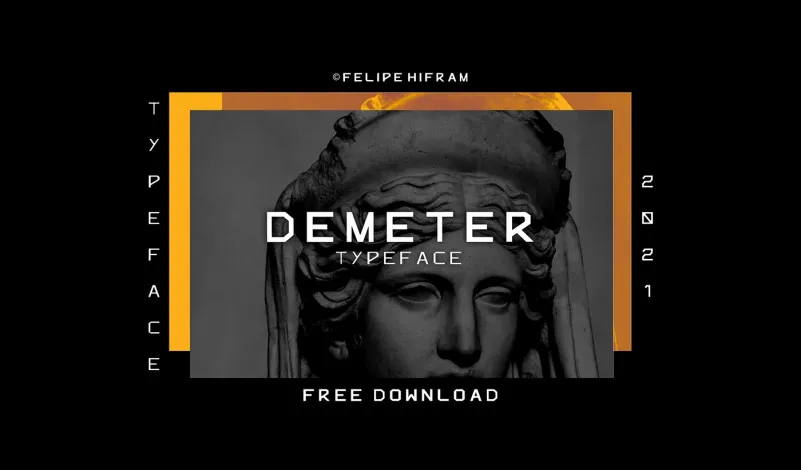
A fonte Demeter Display é uma criação audaciosa do designer Felipe Hifram, projetada para um público que aprecia a fusão entre modernidade e tecnologia. Conhecida por seu estilo futurista, essa fonte se destaca pela sua versatilidade, apta a transformar qualquer design em uma verdadeira obra-prima. Perfeita tanto para aplicação em t-shirts e roupas esportivas quanto para criar logos e anúncios impressionantes, Demeter Display é o elemento gráfico ideal para designers buscando trazer um toque inovador à sua proposta visual. Seja ela a aposta certa para quem busca dar um novo impulso aos seus projetos de design em têxteis, publicidade ou qualquer outro giro do mercado que exige uma personalização única e impactante.